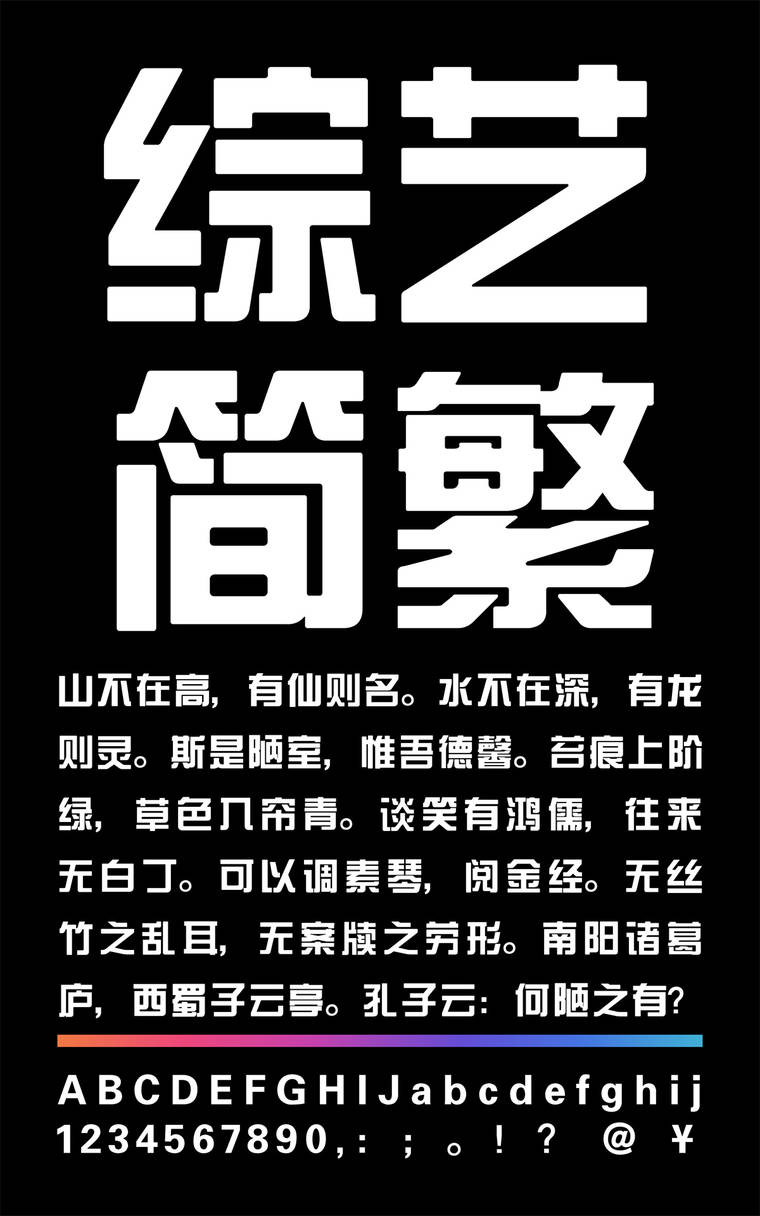
锐字云字库综艺简繁
锐字云字库综艺简繁,这款字体结构工整、笔画清晰,兼顾美观与易读性,适用于标题、正文、海报、包装、LOGO 等多种场景。字形优雅稳定,风格百搭耐看,适配日常排版与创意设计,让文字呈现更舒适、更具质感。锐字云字库综艺简繁一笔一画,皆是细节,以均衡的比例、流畅的线条打造舒适视觉体验,字形端正大气,风格简约现代。无论是商业设计、品牌宣传还是日常排版,都能轻松驾驭,让文字更有格调与力量。锐字云字库综艺简繁字体下载。
字体特征:字体笔画较粗、横平竖直、不失规矩尽量将空间充满,同时为了美观,对拐弯处的处理较为圆润、方正,字体整体体现出活泼严谨,艺术性颇强。